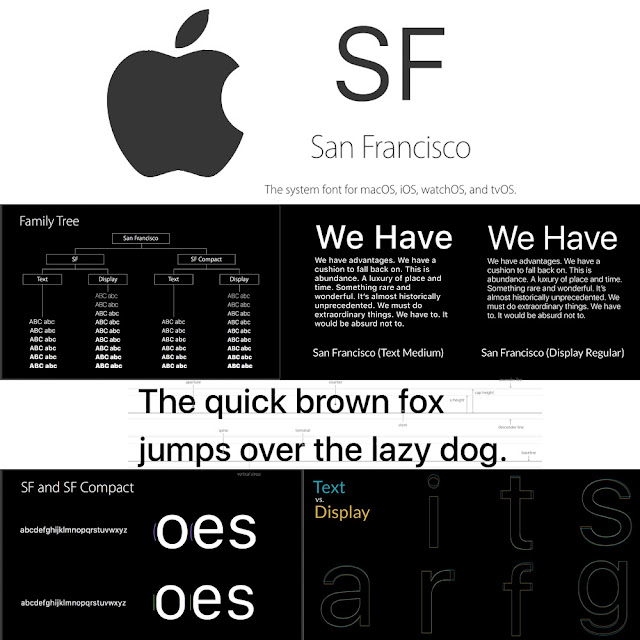
Зачем Apple придумали и ввели в iOS новый шрифт San Francisco? / Хабр
Apple использовала набор шрифтов Helvetica в качестве системного шрифта для iOS с момента выпуска первого iPhone. Они также заменили им Lucida Grande в Mac OS X, начиная с версии 10.10 Yosemite. Так почему же теперь Apple решила избавиться от самого любимого в мире шрифта?
iOS 9 стал официально доступен для всех, и новое семейство шрифтов под названием San Francisco ненавязчиво заменило Helvetica Neue.
Helvetica (слева) и San Francisco (справа)
К этому моменту они уже использовались в Apple Watch. Теперь же San Francisco стал единым стандартным шрифтом для всех продуктов платформы: Apple Watch, iPhone, iPad и Mac.
Apple использовала семейство Helvetica в качестве системного шрифта для iOS с момента выпуска первого iPhone. Они также заменили им Lucida Grande в Mac OS X, начиная с версии 10.10 Yosemite. Так почему же теперь Apple решила избавиться от самого любимого в мире шрифта?
Малые размеры — слабое место Helvetica
Существует мнение, что Helvetica не подходит для текстов малых размеров.
“Helvetica sucks” из блога Erik Spiekermann.
В малой читабельности Helvetica вы можете убедиться следующим образом. Наберите текст малого размера и «размойте» его. Некоторые его фрагменты при этом «смешаются» так, что разобрать их содержимое станет сложно. Говорят, Apple разработала семейство San Francisco как раз для того, чтобы сделать текст малого размера в Apple Watch более разборчивым.
Однако разрешение современных умных устройств превышает разрешение печатного издания, и тексты в iPhone далеко не всегда также малы как в Apple Watch. Почему тогда Apple произвела замену не только в Apple Watch, но и в iOS and Mac OS X?
San Francisco — разнообразен
У шрифтов San Francisco много особенностей, которые делают их удобными для чтения. На самом деле, вариант San Francisco для Apple Watch и вариант для iOS/Mac — два разных шрифта.
Семейство шрифтов под названием “SF” используется для iOS/Mac, в то время как для Apple Watch используется “SF Compact”. Разницу вы можете заметить на примере округленных букв, таких, как ‘o’ и ‘e’. Вертикальные линии в SF Compact сделаны более плоскими, нежели у SF.
Эта разница приводит к тому, что в тексте, набранном с помощью SF Compact, увеличиваются отступы между символами, что в результате делает текст более разборчивым при его чтении с устройств малого размера, таких, как Apple Watch.
В добавок к этому, каждое из семейств подразделяются еще на два подсемейства: “Text” и “Display”. В Apple это называют “Optical Sizes”. Подсемейство Text предназначены для текстов малого размера, тогда как Display — для больших размеров.
Семейство шрифтов San Francisco
Как упоминалось выше, у гротесковых шрифтов (или рубленных), таких как Helvetica, две расположенные рядом буквы «смешиваются», а такие буквы, как ‘a’, ‘e’, ‘s’ становятся очень похожими друг на друга при малых размерах текста.
Сравнение отступов между символами в шрифтах подсемейств Display и Text
Сравнение шрифтов подсемейств Display и Text на примере отдельного символа
Подсемейство Text, при этом, задумано так, что отступы между символами в нем увеличены по сравнению с символами подсемейства Display, а просветы в них расширены для улучшения читабельности при малых размерах текста.
San Francisco динамичен
Одна из замечательных особенностей San Francisco заключается в том, что гарнитура оптимизируется динамически. Display и Text заменяют друг друга в соответствии с размером отображаемого текста. В качестве порога здесь определен размер 20pt.
Дизайнерам и инженерам не нужно беспокоиться о выборе подходящего варианта из семейства. Всего лишь добавляем системный шрифт в UILabel, например. Система сама определит какая гарнитура вам нужна.
Однако по настоящему впечатляет в шрифтах San Francisco то, как в них отображаются двоеточия.
Автоматическое выравнивание двоеточия вертикально по центру
San Francisco пришел к нам из цифровой эпохи
Как видите, шрифты San Francisco созданы и продуманы для легкого восприятия текста любых размеров и на любом устройстве.
Helvetica, на смену которой они пришли, была создана в Швейцарии в 1957 году, когда еще не существовало никаких цифровых устройств. Она, тем не менее, до сих пор используется многими компаниями в качестве корпоративного шрифта, и, вне всяких сомнений, будет использоваться и в будущем как хороший классический шрифт.
San Francisco же, напротив, является шрифтом современным. Его гарнитура меняется динамически, в соответствии с контекстом.
Его можно назвать своего рода «родным шрифтом» цифровой эпохи.
Ubuntuдля Linux -
Fira Sansдля ОС Firefox - Для эмодзи